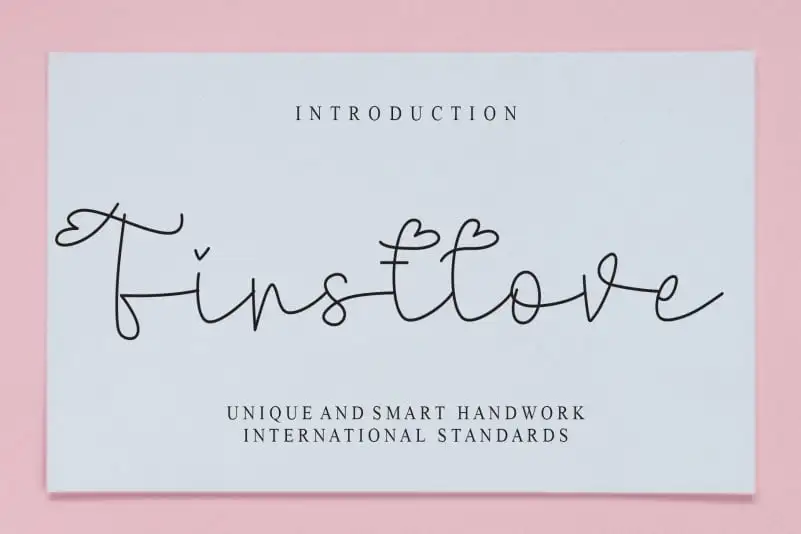
Firstlove Handwritten Font – Fonte Grátis
Firstlove Handwritten Font
Aqui está uma descrição em português para a página de download da font ‘Firstlove Handwritten Font’, seguindo as instruções: Sinta-se seduzido pela ‘Firstlove Handwritten Font’. Esta fonte é perfeita para quem busca um toque delicado e autêntico nas mensagens digitais. Criada por designers talentosos, esta mão-d escrita vai transformar qualquer texto em algo pessoal e único. Com um design envolventemente natural e uma caligrafia fluida, a ‘Firstlove Handwritten Font’ é perfeita para criar mensagens suaves e leves, ou para expressar sentimentos mais intensos com sua textura única. Compreender o poder de transmitir emoções através das letras escritas à mão é um privilégio que esta font oferece a todos os usuários. Ideal tanto para personalizar seu site ou blog quanto para criar mensagens pessoais e emotivas no seu próximo projeto, ‘Firstlove Handwritten Font’ é uma escolha inteligente para aqueles que valorizam o charme da autenticidade. Tente agora!